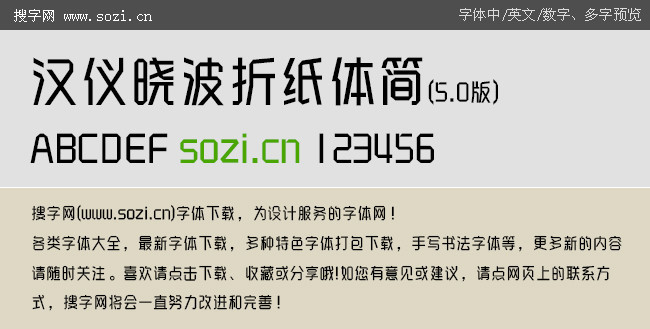
漢儀曉波折紙體簡5.0
搜字網(wǎng)提供一款漢儀曉波折紙體簡5.0字體下載,漢儀曉波折紙體是一款漂亮的藝術(shù)字體。由漢儀曉波工作室出品,漢儀曉波折紙體是一款字形瘦高的字體,每個筆畫都處理成了紙張折疊的效果,因此具有很強的趣味性和設(shè)計感,又兼具現(xiàn)代感,是一款品質(zhì)優(yōu)良的美術(shù)字形。(本字體為個人非商用版,如需要商用請聯(lián)系漢儀公司購買版權(quán))